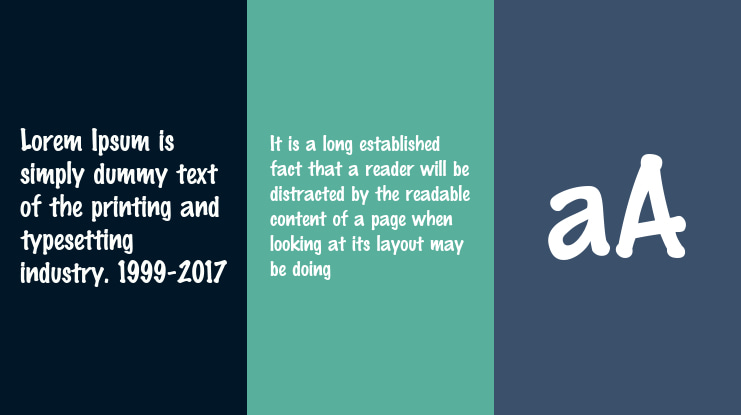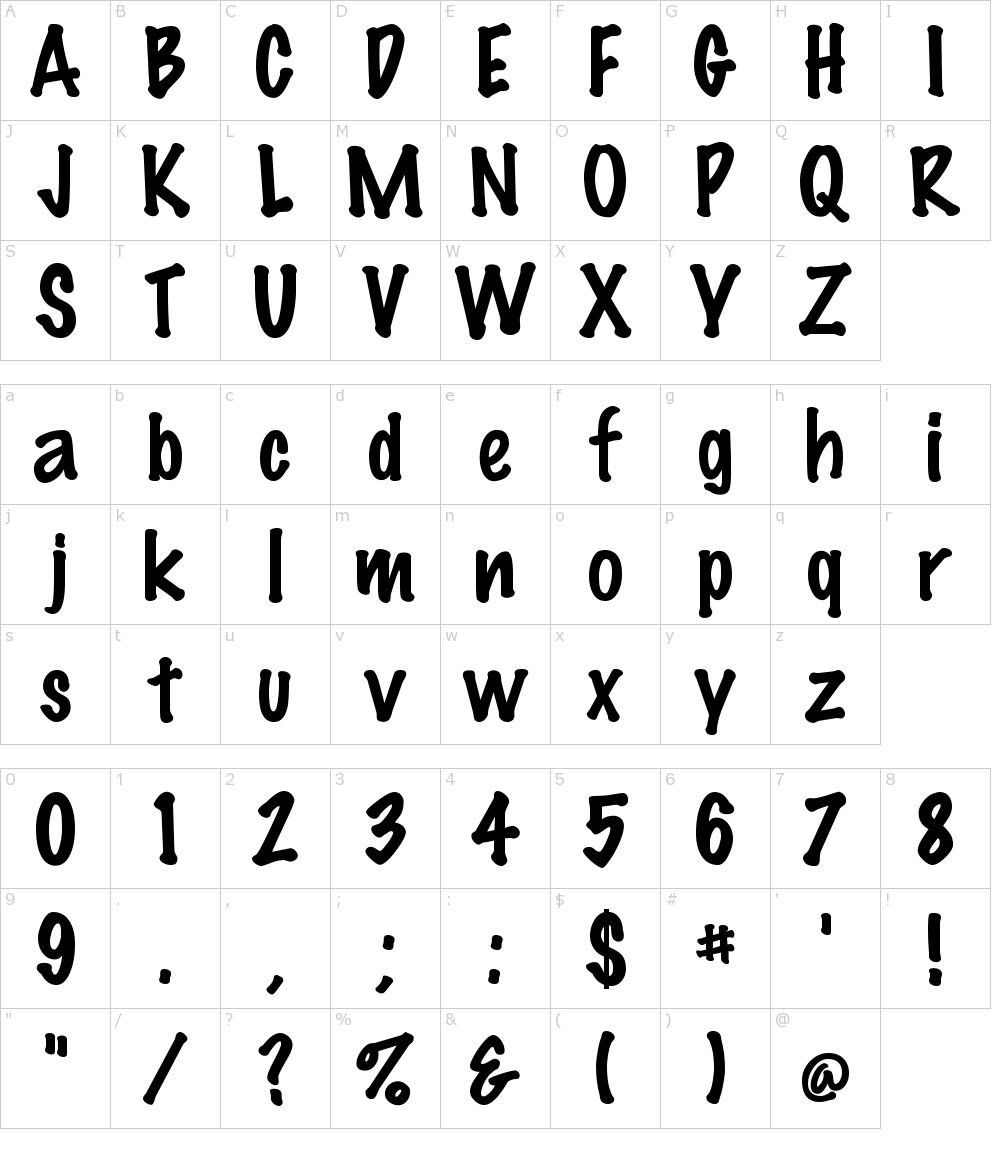
Nhiều người gặp rắc rối khi tìm tải Marker Felt Font Việt hóa nhưng bị lỗi hiển thị các nét xước hoặc không gõ được dấu tiếng Việt chuẩn. Những sai sót kỹ thuật này khiến các poster sự kiện, nhãn dán thủ công trở nên kém thẩm mỹ, làm giảm sự hào hứng của người xem. Xưởng In Viva cung cấp bản tải font Marker Felt Việt hóa sắc nét, đã tối ưu đường path hỗ trợ in ấn tem nhãn rực rỡ.
Lưu ý: Marker Felt Font có đặc trưng là các nét bút không đều. Khi in ấn trên chất liệu vải nhám, bạn nên kiểm tra xem các vết xước nhỏ có bị mất nét không để điều chỉnh độ dày chữ phù hợp.
Ứng dụng font Marker Felt trong in ấn và sản xuất bao bì
Phong cách tự do của Marker Felt mang lại vẻ ngoài đầy sáng tạo và phá cách cho các ấn phẩm của doanh nghiệp:
- Thiết kế tem nhãn dán sản phẩm Handmade: Marker Felt cực kỳ phù hợp để in nhãn cho hũ mứt, nến thơm hoặc xà phòng thủ công, tạo cảm giác thân thiện và chân thành.
- Sản xuất bao bì hộp bánh kẹo thiếu nhi: Những nét chữ nghịch ngợm in trên hộp giấy Ivory tạo sự hào hứng cho các bé ngay từ cái nhìn đầu tiên.
- Khắc laser ấn phẩm lưu niệm bằng gỗ: Chữ Marker Felt khi khắc trên bìa sổ gỗ hoặc hộp trà gỗ tạo hiệu ứng cháy cạnh vô cùng bụi bặm và phong cách.
- Trang trí voucher và thẻ cứng: Một lời chúc viết bằng font Marker Felt giúp tấm thẻ trở nên ấm áp và bớt đi vẻ công nghiệp cứng nhắc.
Sử dụng font chữ Marker Felt cần lưu ý gì?
Để họa tiết chữ bút dạ này hiển thị đẹp trên thành phẩm thực tế, designer cần chú trọng:
- Kiểm tra hệ màu CMYK chuẩn: Với phông chữ bút dạ, bạn nên sử dụng các tông màu đậm (như xanh than, đỏ sẫm) để mô phỏng chính xác màu mực của bút Marker.
- Tối ưu đường Path cho gia công bế nổi: Vì Marker Felt có nhiều đường uốn lượn và nét xước tự do, bạn cần xử lý sạch điểm neo dư thừa để khuôn bế không bị giật khi dập nổi logo.
- Lưu ý độ tương phản: Font này chỉ thực sự đẹp khi có độ tương phản cao giữa chữ và nền. Tránh in chữ Marker Felt màu nhạt trên nền giấy nhám màu xám hay Kraft nâu nhạt.